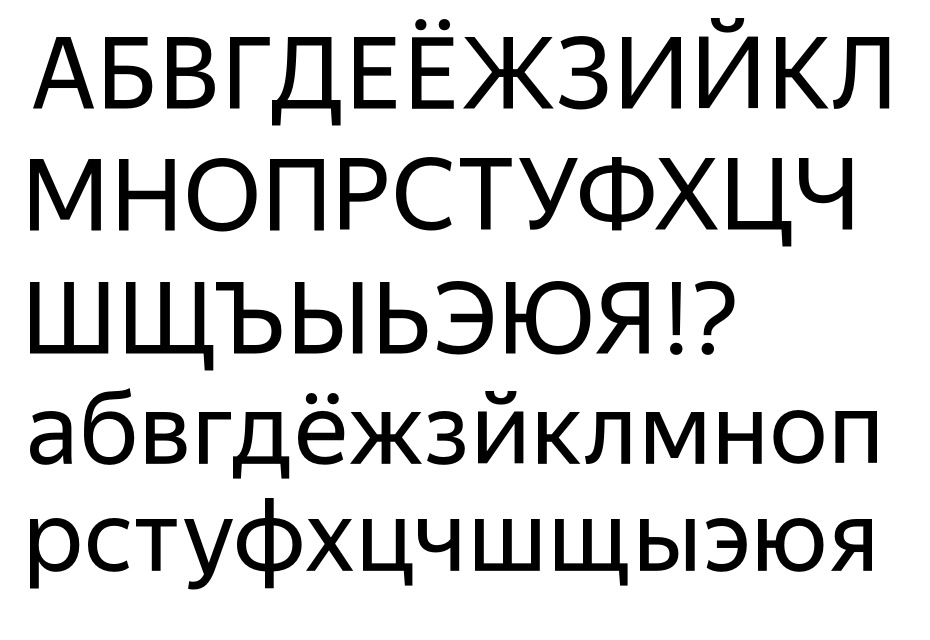
печатный шрифт — это… Что такое печатный шрифт?
ШРИФТ — ШРИФТ, а, мн. ы, ов и ы, ов, муж. Форма письменных или печатных знаков. Печатный, рукописный, рисованный ш. Рисунок шрифта. Наборный ш. (полученный в результате типографского набора). Типографский ш. (комплект литер и других элементов для набора) … Толковый словарь Ожегова
ПЕЧАТНЫЙ — ПЕЧАТНЫЙ, ая, ое. 1. см. печатать. 2. Напечатанный, появившийся в печати. П. отзыв о спектакле. 3. Применяемый в печати, в печатании. П. знак. 4. О прянике: с тиснением.
• Печатные буквы имитирующие прямой печатной шрифт. Толковый словарь Ожегова … Толковый словарь Ожеговашрифт — графическая форма знаков определённой системы письма; в узком смысле слова – комплект типографских литер, предназначенный для набора. При наборе текстов используют шрифты разного рисунка (печатный, рисованный), различных начертаний (курсивный,… … Энциклопедия техники
шрифт — а, мн. шрифты и шрифты, м. 1. Комплект типографских литер (букв, знаков препинания, математических и других знаков), необходимых при наборе какого л. текста. Привезли наборщики с рассветом семь шрифтов, семь касс, печатный станок. Берггольц,… … Малый академический словарь
- Полуустав (шрифт) — У этого термина существуют и другие значения, см. Полуустав (значения). Лаврентьевская летопись (1377) Полуустав форма … Википедия
Гражданский шрифт — шрифт, который начали применять в России в книгах гражданской печати в результате проведённой в 1708 Петром I реформы (взамен прежнего древнерусского шрифта).
Первой книгой, набранной Г. ш., была «Геометриа славенски землемерие» (1708).… … Большая советская энциклопедияГражданский шрифт — «Геометриа славенски землемерие» первая книга, набранная гражданским шрифтом … Википедия
Type font — Шрифт; Комплект шрифта; Печатный шрифт … Краткий толковый словарь по полиграфии
РОНДО — (фр., от rond круглый). 1) лирическое стихотворение в тринадцать стихов, с двумя рифмами. 2) музыкальная пьеса, в которой главная тема или первая мысль часто повторяются. 3) круглый рукописн. шрифт. Словарь иностранных слов, вошедших в состав… … Словарь иностранных слов русского языка
Описание:Правильные русские шрифты для игры Skyrim SE. Идея этого мода в том, что русских шрифтов для игры Skyrim Special Edition создано не так много. Я протестировал все популярные наборы шрифтов в игре, и каждый набор в чём то меня не устроил, поэтому я решил исправить эти ошибки в популярных шрифтах (читаем ниже), создав свой набор, названный «Правильные русские шрифты».
Ошибка № 1. Отсутствие букв русского алфавита «ё» и «Ё», отсутствие некоторых символов пунктуации, например квадратных кавычек и длинного тире.
Извините, но уже 27 лет, как существует Unicode, поддерживающая все национальные алфавиты и символы пунктуации. К 2019 году создана масса юникодных шрифтов. И, наконец, сам движок Skyrim SE имеет поддержку юникода. Вследствие этого, тексты книг и записок многих модов, которые содержат эти символы (в том числе мои переводы), будут забагованы — вы увидите квадраты вместо букв, либо строки текста будут наезжать друг на друга.
Ошибка № 2. Баг русской консоли, который Bethesda не соизволила исправить за 8 лет после первого выхода игры.
Ошибка № 3. Несоответствие размера шрифта его назначению. Шрифт в наборе шрифтов настроен, как шрифт меню, но в игре я вижу, что он слишком широк для меню. Это легко проверить. Например, установив Sovngarde, я вижу в режиме скрытности сообщение: «Вас не», «Вас», вместо правильного варианта «Вас не видят», «Вас заметили».
* Все это исправляется моим модом.
Говоря о толщине штриха планки / чаши, может быть, было бы неплохо сделать Њ планку немного тоньше, чем полоску H, а верхнюю чашу горизонтально Њ немного тоньше, чем в Ь, особенно при более толстом шрифте, чтобы избежать скопления черного на этом «4-лучевом» пересечении.